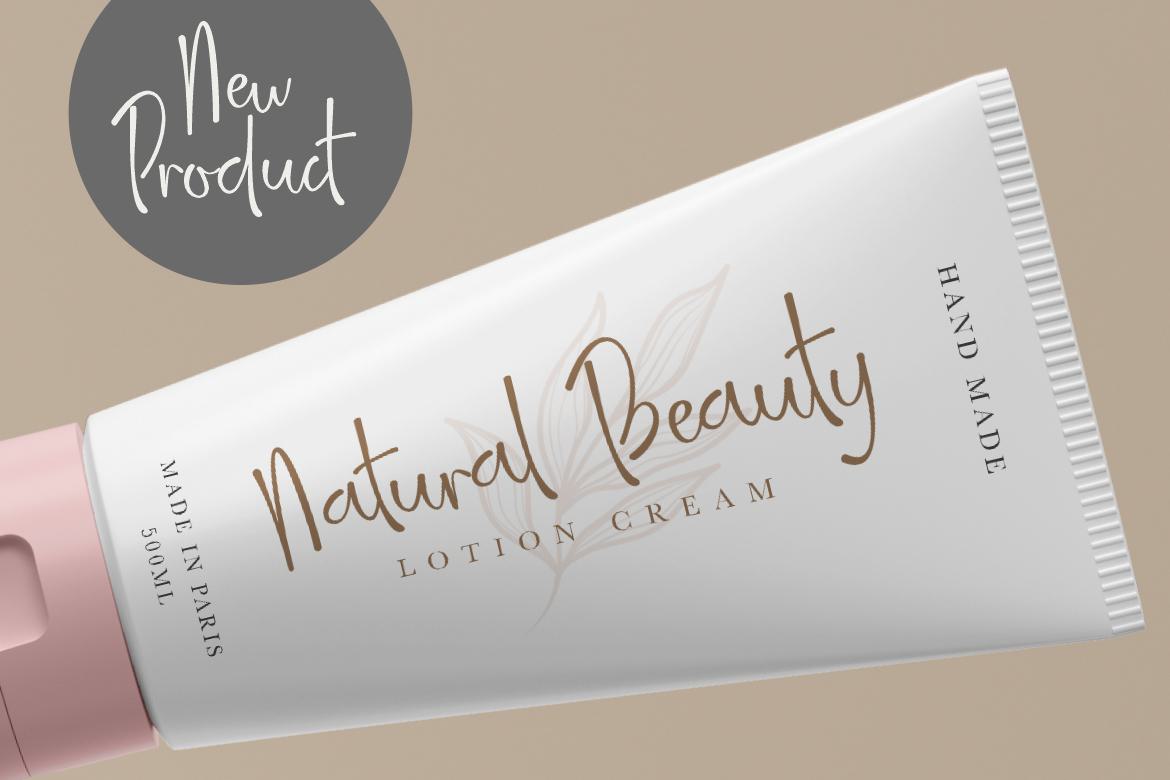
Amellainkis Abeautiful、Femininea和Natural以及Write Tenscript字体。该字体中还提供了几种可选字体。该字体适用于创建徽标、水印、品牌、婚礼宣传、报价或任何内容。让我们使用此字体创建一些美丽的项目。Amellainkis Abeautiful,女性、自然和书写字体。此字体中还提供了几种可选的清洗字体。此字体非常适合创建徽标、水印、品牌、婚礼宣传、报价或任何内容。让我们用此字体创建一些美丽的项目。